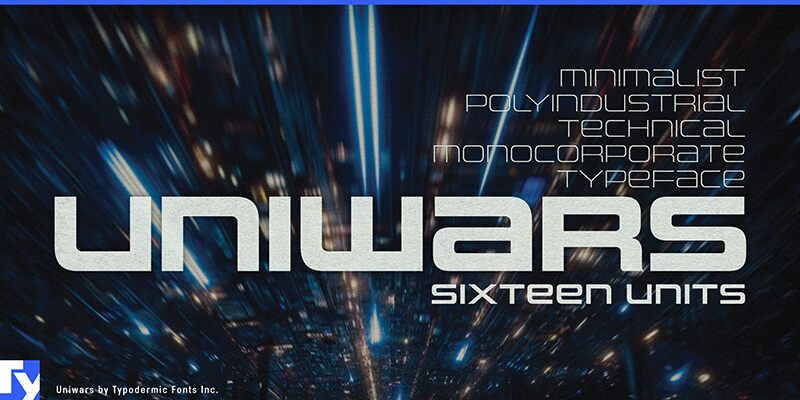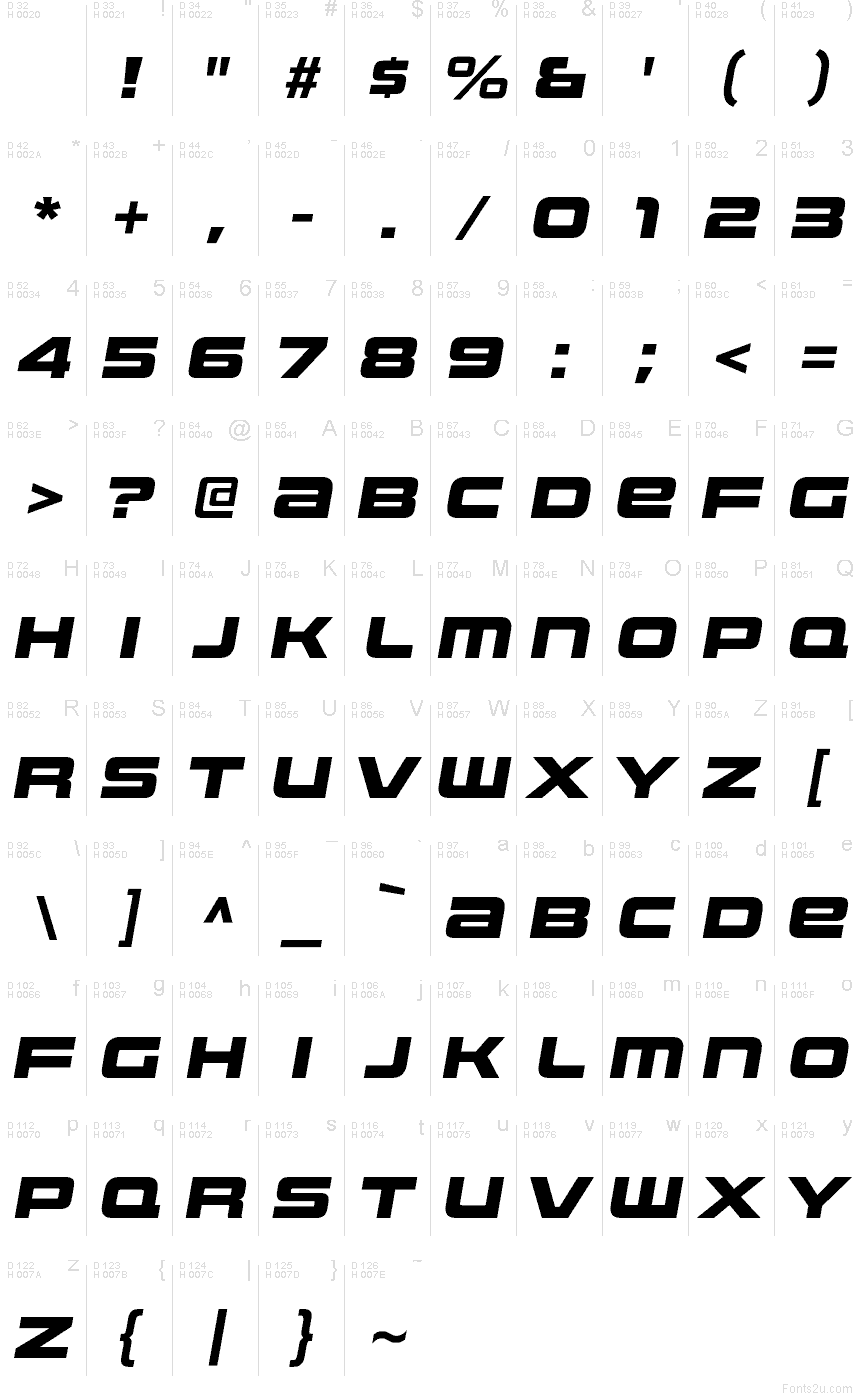
Uniwars Heavy Italic
Uniwars Heavy Italic von Typodermic Fonts Inc. ist eine futuristische Display-Schrift, die mit ihrem dynamischen Sci-Fi-Look und massiven, modellierten Buchstaben besticht. Die Formen wirken wie aus einem Guss: Breite Striche, abgerundete Außenecken und präzise horizontale Schnitte verleihen dem Alphabet eine schnittige Ästhetik, die an die Armaturen eines futuristischen Fahrzeugs erinnert, statt in kalte Klischees zu verfallen.
Die Schrift eignet sich ideal für Gaming-Logos, E-Sports-Grafiken, Plakat-Überschriften, Album-Cover und Titelkarten, bei denen Dynamik im Vordergrund steht. Als kostenloser Font lässt sie sich hervorragend für prägnantes Branding, Interface-Elemente und Verpackungsdesigns einsetzen – besonders dann, wenn die Typografie puren Vorwärtsdrang ausstrahlen soll.